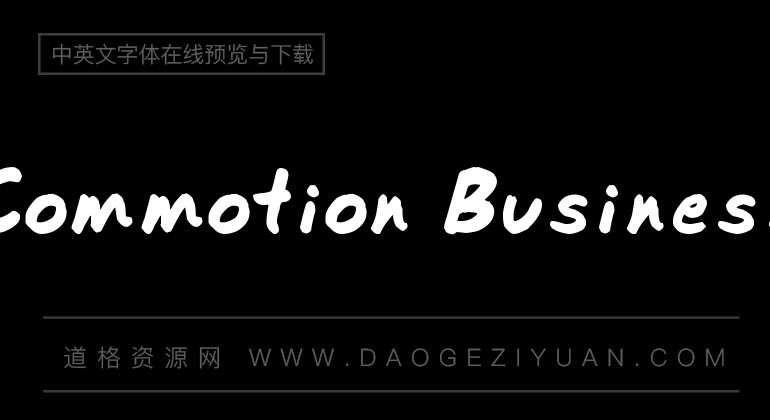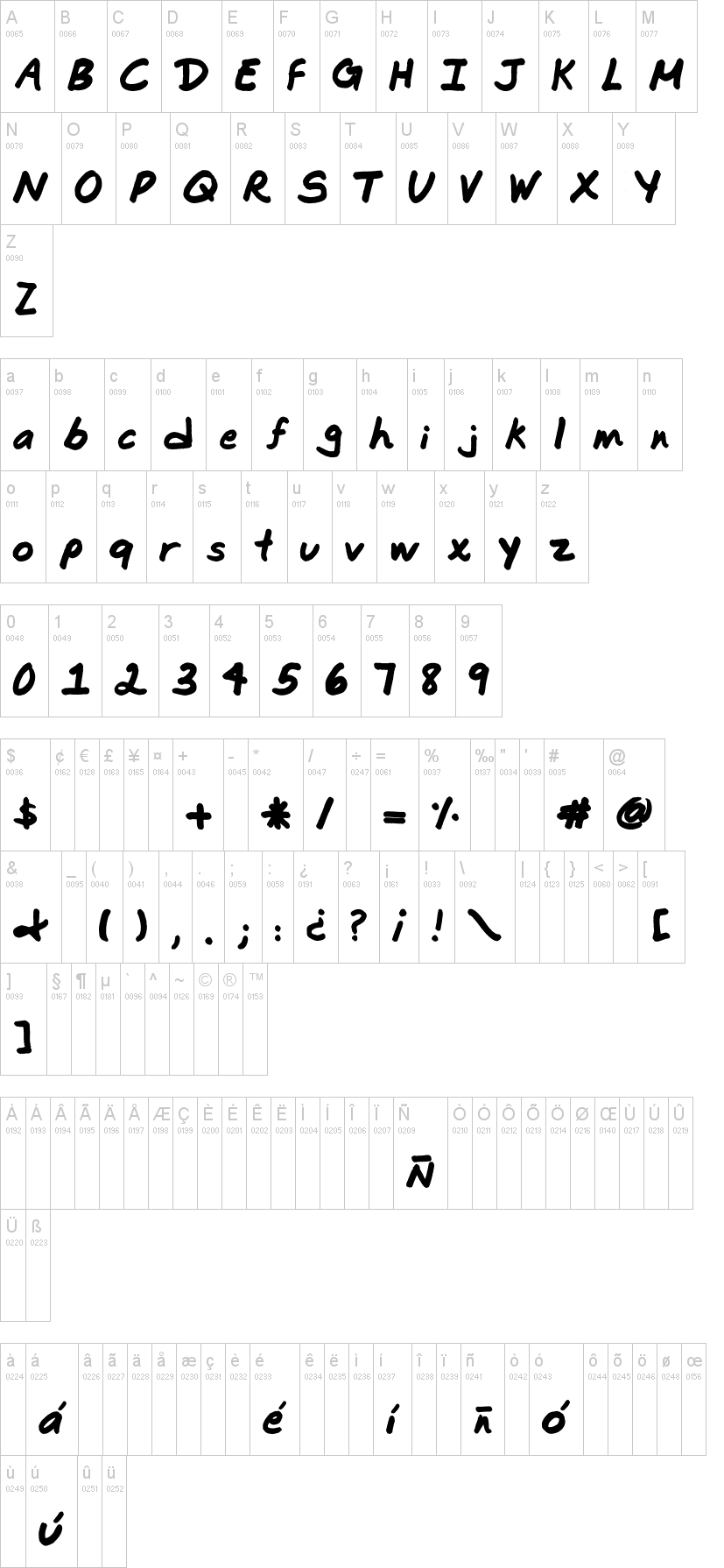
Commotion Business
? Commotion Business 字体是一款清新大气的商业字体,它具有极具特色的外观,拥有较高美感,是商业网站、广告、宣传册、品牌形象等的理想选择。Commotion Business 字体的字形清晰,笔画柔和,线条流畅,给人以轻快、活泼的感觉,适用于各种商业场景,是商业网站、广告、宣传册、品牌形象等的理想选择。
Commotion Business是一款非常不错的手写艺术字体,具有很好的视觉感,适合于文化类的宣传设计、商业类品牌的广告和产品包装设计以及个性化文字排版等较多场景。
Commotion Business字符映射图